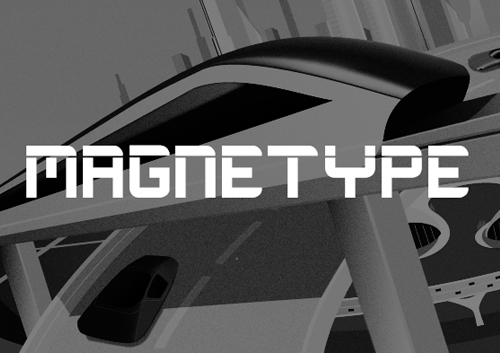
Magnetype é uma fonte em caixa alta inspirada por filmes de ficção científica que pode ser usada em títulos e frases curtas, foi desenvolvida para um projeto acadêmico que consistia na criação de uma tipografia para uma empresa de monotrilhos fictícia.